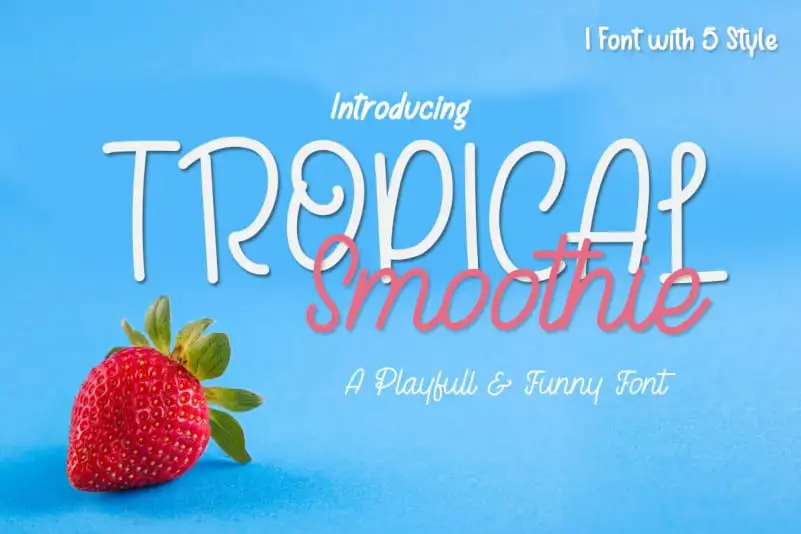
Tropical Smoothie Script Font – Download Grátis
A fonte ‘Tropical Smoothie Script Font’ é uma variação natural da calligrafia que transmite sensações frescas e alegres, perfeitamente adaptada para ambientes leves e divertidos. Idealmente projetada para aplicar elementos tropicais em designs de arte gráfica, esta fonte traz com ela um toque suave e leve caracterizado por traços fluidos e elegantes, perfeita para criar um visual envolventemente agradável. Para quem busca uma maneira criativa de introduzir elementos leves e vibrantes em seu design, ‘Tropical Smoothie Script Font’ oferece o ideal para tornar sua criação ainda mais sofisticada e encantadora, sem perder o toque tropical único que faz desta fonte uma escolha inigualável no mercado.
Designer: mhdafifersya